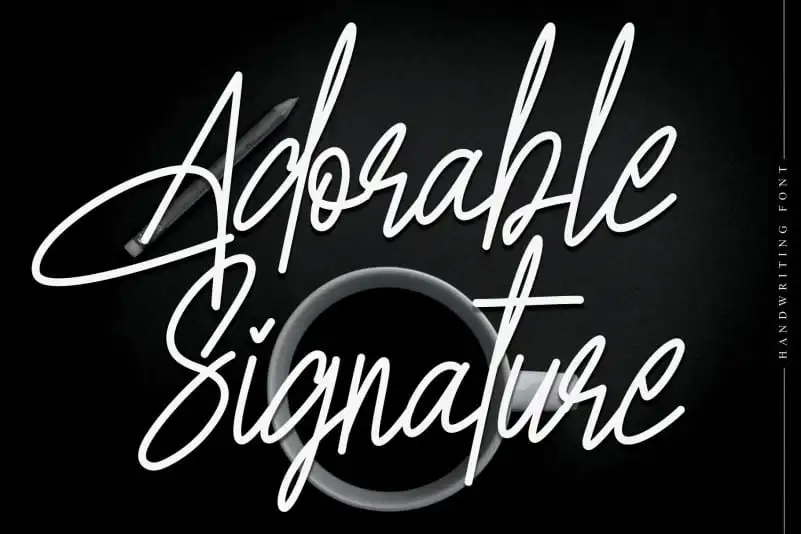
Adorable Signature Handwritten Font – Fonte Grátis
Adorable Signature Handwritten Font
Descubra uma nova opção para seus projetos digitais com a ‘Adorable Signature Handwritten Font’. Essa linda fonte foi criada pelo designer CreativeLetter especialmente para oferecer um gosto especial e único aos designers devido à sua exuberância de detalhes e naturalidade. Seja ela usada em assinaturas, cartões de aparição ou até mesmo em mensagens individuais, essa fonte adorável vai fazer seu trabalho de forma única. Não apenas é uma excelente escolha para quem gosta de criar um toque pessoal em suas produções digitais, mas também oferece a oportunidade de explorar o poder do design original e criativo, mantendo sempre esse ar delicado e acolhedor que torna todas as criações mais únicas.